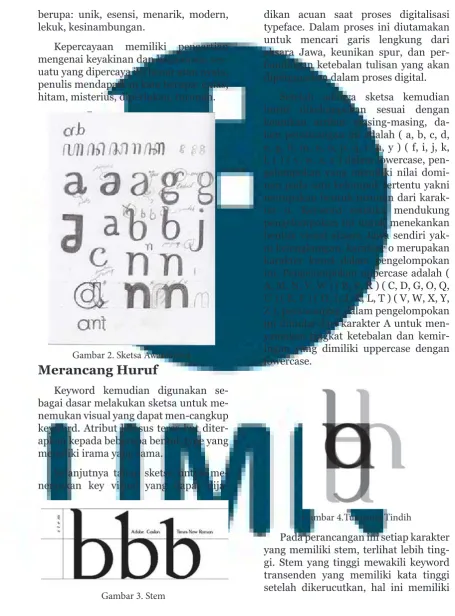
bagian dari perkembangan tipografi modern Indonesia. Namun tidak banyak desainer tipogra
-fi Indonesia memunculkan karya dengan Aksara Jawa sebagai stimulinya, sehingga tidak ban -yak, bahkan jarang typeface Indonesia yang mengangkat akar budaya Nusantara sebagai
pon-dasi tipografi Indonesia. Perancangan ini diharapkan dapat memadukan aksara Jawa dengan perancangan tipografi modern, sehingga memunculkan typeface sebagai identitas Indonesia, adapun hasil akhir berupa perancangan font dan type specimen book.
Kata kunci: typeface, tipografi, aksara Jawa, kebudayaan Indonesia
Pendahuluan
Aksara Pallawa dan bahasa Sanse-kerta adalah bagian yang mempengaruhi ban-yak terhadap perkembangan Aksara Nusantara yang kita kenal sampai seka-rang ini.
Penggunaan huruf latin dalam ko-munikasi sehari-hari di Indonesia men-jadikan aksara Jawa terlupakan. Hal ini sangat disayangkan dikarenakan aksara Jawa adalah artefak leluhur yang
memi-liki filosofi kuat dan merupakan bagian
berharga dari sejarah Indonesia. Aksara Jawa memiliki sejarah dan hubun-gan yang kuat denhubun-gan Yogyakarta yang memiliki kearifan lokal yang beragam dari cerita rakyat, seni tari, wayang, dan masih banyak lagi. Aksara merupakan sebuah sistem tulisan yang digunakan
manusia untuk berkomunikasi yang dalam bahasa Indo-nesia mengandung makna lain sebagai sinonim huruf.
Huruf yang digunakan dalam dun-ia digital sekarang ini disebut sebagai
typeface. Typeface merupakan salah satu komponen utama dalam penyam-paian pesan, selain memperjelas pesan yang disampaikan pemilihan typeface
yang tepat juga dapat menyampaikan emosi dan ekspresi, memiliki warna yang berbeda-beda, dan juga memberi-kan kesan simbolik seperti contoh font
yang digunakan pada graffiti dan mural.
Gambar 1. Aksara Jawa
ditulis Suryo Sukendro, dan sebagainya yang menggunakan typeface seadan-ya. Hal ini menunjukan kurangnya text
typeface secara spesifik, padahal Indo -nesia yang memiliki kekayaan kultur dan budaya yang tidak terbatas. Oleh karena itu diperlukan sebuah typeface latin adaptasi aksara Jawa yang aplikatif dalam kegiatan komunikasi dengan tu-juan melestarikan aksara Jawa. Peneli-tian dibatasi dengan jenis typeface yaitu text typeface dimana text typeface dapat dipergunakan di berbagai jenis litera-tur yang sesuai dengan tujuan komuni-kasi. Esensi dari perancangan typeface
adalah menterjemahkan bahasa lisan menjadi visual dengan tingkat keterb-acaan yang baik, yang dirancang sesuai dengan data yang dihasilkan penulis. Penggunaan typeface pada berbagai je-nis literatur memiliki tujuan melestari-kan aksara Jawa, dan juga bentuk dari setiap alfabet akan menghasilkan emosi dan warna tertentu yang juga dapat
di-gunakan oleh para desainer grafis dalam
merancang desain yang dirasa memiliki mood yang sesuai dengan typeface.
Rumusan Masalah
Berdasakan uraian latar belakang di atas, maka dapat dirumuskan adalah
bagaimana merancang tipografi sebagai
text typeface yang berdasarkan adaptasi aksara Jawa?
Metodologi
Perancangan ini mengharuskan un-tuk memahami peristiwa atau keadaan yang sedang terjadi secara lengkap dan natural, sehingga metode deskrip-tif tepat digunakan dengan alasan un-tuk menyampaikan metode yang ber-langsung dari kurun waktu tertentu sampai sekarang (Naibaho, 1998, hlm 38). Dibutuhkan data primer melalui wawancara dengan responden terpilih, dalam penelitian ini adalah desainer
grafis terpilih yang penulis rasa merupa -kan responden yang tepat bagi peneli-tian ini, selain wawancara penulis juga melakukan observasi di Yogyakarta dan literatur yang terkait. Data sekunderpun dibutuhkan melalui angket dan dibu-tuhkan pula studi exsisting.
Pada wawancara dengan Narto, salah satu budayawan yang mengab-di pada Museum Negeri Sonobudoyo menceritakan tentang asal-usul aksara Jawa yang ditenggarai sebagai pence-tus aksara Jawa. Dalam wawancara
keya-kinan yang dipercaya oleh masyarakat sebagai tolak bala atau mengusir hantu. Beliau juga mengatakan bahwa aksara Jawa sudah mulai dilupakan oleh banyak orang, hanya para pelajar yang mempe-lajari sastra Jawa yang masih mengeta-hui dan bisa meneruskan aksara Jawa, bahkan bapak Narto mengatakan bahwa untuk meraih gelar magister mengenai sastra Jawa dibutuhkan studi lanjut ke Belanda, disini tidak mampu. Menurut beliau nilai yang terkandung merupa-kan suatu kesatuan yang melambangmerupa-kan aksara Jawa itu sendiri. Sebuah falsafah masyarakat Yogyakarta dari Tugu sampai Kraton “Sangkangkaraning”. Sangkang-paran yang merupakan lingga dan yoni
ada di Tugu, merupakan filosofi bagaima -na lahirnya kota Yogyakarta. Di dalam Kraton ada sebuah bangsal bernama bangsal Witono yang memiliki bangsal lebih kecil bernama mangunturtangkil merupakan tempat Sri Sultan duduk dan menghadap ke utara atau ke arah Tugu. Bangsal tersebut di-percaya merupakan sebuah jalan ke-hidupan, yakni ada alun-alun lalu ada perempatan yang menunju-kan mau ke arah mana manusia beran-jak. Lalu ada tiga godaan yang dipercaya oleh masyarakat Yogyakarta yaitu harta, tahta, dan wanita dimana pasar paring-harjo merupakan godaan harta, kantor gubernur merupakan godaan tahta, dan pasar kembang merupakan godaan wani-ta. Hal ini merupakan hal yang dipercaya masyarakat Yogyakarta yang ada dari dulu sampai sekarang.
kearifan Nusantara aksara Jawa sendi-ri. Selain universal typeface juga dapat merepresentasikan aksara Jawa dan se-cara tidak langsung menyampaikan latar belakang terbentuknya typeface kepada penguna sehingga upaya melestarikan aksara Jawa dapat terwujud.